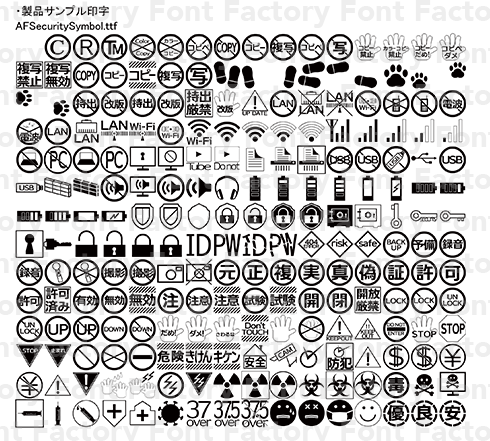
「AFSecuritySymbol」は、セキュリティ関連のシンボルフォントです。太字の和文フォントである「AF-UVImpact」との相性もよく混植でも違和感がありません。マニュアルなどドキュメントにも最適です。
※「AFSチェックライター風 漢字版フォント」に含まれていたシンボルを抜粋し新規に追加したシンボル専用フォントです。